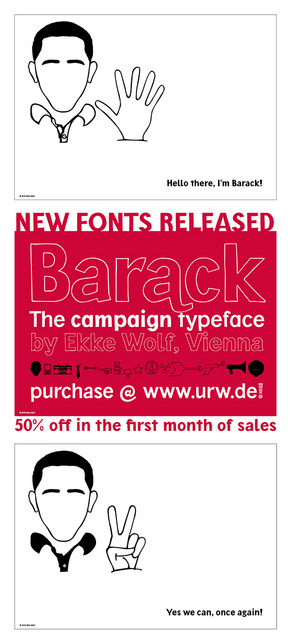
neue Schrift: Barack
soeben ist meine neue Schrift "Barack" erschienen, zu betrachten und zu erwerben bei www.urw.de.
Sie ist als Folgeprojekt eines handgezeichneten Buchumschlags entstanden. Barack Outline wurde mit einem 0,5 mm Faserschreiber auf Transparentpapier gezeichnet, die Schnitte Bold und Medium entstanden daraus am Mac.
Das Fontediting habe ich erstmals komplett auf Glyphs von Georg Seifert erledigt -- Kompliment und heiße Empfehlung!
Die Schrift ist eine Hommage an Barack Obama, gedacht für größere Schriftgrade, speziell in der zarten Outline. Ich hoffe, sie gefällt euch.
Was mich aus reiner Neugier völlig unabhängig von der Schrift mal interessieren würde: Wie kommt eigentlich man auf die Idee, einen Font als Hommage an Obama zu bezeichnen? Hat die Schrift irgendwas mit Obama zu tun? Ist der amerikanische Präsident so ein Held für Dich, daß Du ihn irgendwie ehren wolltest ( - und wenn dem so wäre, würde ich gern erfahren, was der gute Obama denn so Eindrucksvolles geleistet hat)? Oder ist das die bestellte Hausschrift für Obamas Wahlkampagne und in Wien ist Obamas Europaagentur?
Und wenn es nix außer möglicherweise persönliche Verehrung für den Mann sein sollte - was ja auch völlig legitim wäre -: Ist es nicht reichlich gewagt, mit dem Namen hausieren zu gehen? Bei der Klagefreudigkeit von Amerikanern meine ich nur ...
Oder gibts gar eine freundliche Genehmigung des Präsidenten?
Völlig unabhängig jeglicher politischer Richtungsmeinung (die ich zwar habe, aber die nicht hierhin gehört): Gibt es eigentlich schon ähnliche Statements in der Schriftenszene? Eine Gandhi Uncial beispielweise könnte ich mir vorstellen, kunstvoll kontrastiert von der Churchill Gothic und der Kennedy Script, die so gar nicht mit der schmalen Castro, der schrägen Gorbatschov, der Mao Heavy oder der breitfetten Strauss harmonieren will ...
Bisher hab ich sowas noch nicht gesehen ...
... breitfetten Strauss harmonieren will ...
Bisher hab ich sowas noch nicht gesehen ...
Ich stelle mir gerade so eine barock verspielte, handgemalerte Bierzeltfraktur vor ...
tl;dr So holzschnittartig wie der Charakter der Schrift sind auch die Klischees, mit denen der Gestalter umher wirft. Eine Hommage ist das nicht.
Wie kommt eigentlich man auf die Idee, einen Font als Hommage an [einen Politiker] zu bezeichnen?
Warum eigentlich nicht? Schriftnamen haben doch relativ oft etwas mit den persönlichen Vorlieben des Gestalters und nichts mit dem Charakter der Schrift an sich zu tun.
Hat die Schrift irgendwas mit Obama zu tun?
Nein! Weder mit der Person noch mit seiner Partei oder US-Wahlkämpfen allgemein. Es ist bekannt, dass Obama schon mindestens seit seiner Zeit als Redakteur der Harvard Law Review Perfektionist ist. Handschriftliches Gekrakel passt zu ihm überhaupt nicht. US-Wahlkämpfe haben eine ganz typische typografische Formsprache. Handgemalte Schriften kommen darin nach meinen Erfahrungen nie vor, nicht mal bei bekennenden Antiestablishmentkandidaten auf der untersten Ebene (was einiges heißen will, stehen hierzulande selbst Dorfbuchhalter, Hundefänger und Abteilungsleiter der Müllabfuhr zur Wahl).
Ist der amerikanische Präsident so ein Held für Dich, daß Du ihn irgendwie ehren wolltest ( - und wenn dem so wäre, würde ich gern erfahren, was der gute Obama denn so Eindrucksvolles geleistet hat)?
Nett, dass du deine Meinung zu Obama nicht zum Thema machst (siehe unten). ;-)
Ist es nicht reichlich gewagt, mit dem Namen hausieren zu gehen? Bei der Klagefreudigkeit von Amerikanern meine ich nur ...
Ne, also davor muss der Gestalter nun wirklich keine Angst haben. Obamas Vorname ist nicht »schützbar«.
Völlig unabhängig jeglicher politischer Richtungsmeinung (die ich zwar habe, aber die nicht hierhin gehört)
Na ein Glück (siehe zwei Zitate weiter oben)! :mrgreen:
Ansonsten finde ich die Klischees, mit denen der Gestalter spielt, nun ja …
Ich habe Obama noch nie das Victory-Zeichen ✌ machen sehen, und das (ursprünglich britische!) CND-Zeichen ☮ hat er als Erwachsener mit an Sicherheit grenzender Wahrscheinlichkeit noch nie benutzt. (Hätte der Gestalter auch nur die geringste Ahnung von amerikanischer Politik, hätte übrigens wenigstens ein Esel dabei sein müssen.) Und dann auch noch der Afro-Kopf (der mich im ersten Moment an eines dieser kugelrunden Schafe erinnert hat, die ich immer in Island sehe)! Das ist bestenfalls peinlich und schlimmstenfalls grenzwertig rassistisch. :-(
Was sagt denn die verehrte Forumsgemeinde ganz unabhängig von der Namensgebung zur hier präsentierten Schrift? Wie gefällt Euch die Schrift an sich – würdet Ihr sie einsetzen und wenn ja für welchen Zweck?
… Wie gefällt Euch die Schrift an sich …
Ich finde sie … hm … ganz nett. Nichts Besonderes, zigmal auf dafont als Freefont vorhanden. Nichts, was ich mir kaufen würde. :-?
Zur Namensgebung: Das Buch, aus dessen Gestaltungsauftrag die "Barack" hervorgegangen ist -- im Endeffekt hat der Verlag noch 2mal den Titel geändert, woraufhin ich das Handtuch geworfen habe --, hatte Obamas Präsidentschaft zum Thema.
Selten so einen Quatsch gelesen.
Bewerte doch einfach die Schrift, wenn du dazu nichts zu sagen hast, sage nichts.
Mir persönlich ist die Schrift ein wenig zu unruhig, und der, zumindest in meinen Augen, leichte "optische Linksdrall" bei einigen Buchstaben - naja... Die Medium gefällt mir von allen am besten.